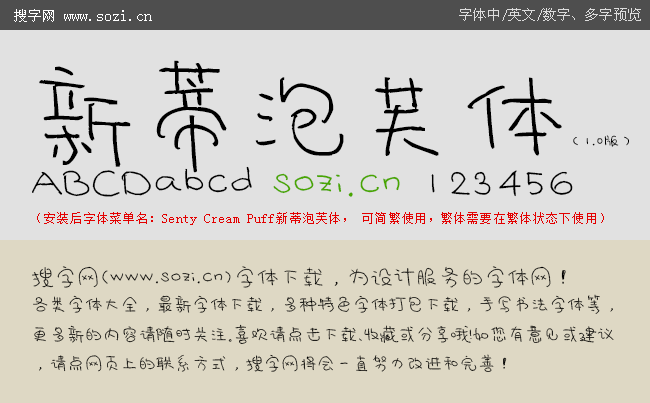
新蒂泡芙體
搜字網(wǎng)提供一款新蒂泡芙體中文字體下載,新蒂泡芙體是一款應(yīng)用于設(shè)計方面的中文簡體漢字,該字體筆畫非常細(xì)膩,整體效果為卡通風(fēng)格,且字庫完整,覆蓋常用簡體、繁體漢字、拉丁字母、數(shù)字等,可用于產(chǎn)品設(shè)計、包裝印刷、報刊雜志、繪畫創(chuàng)作等廣告設(shè)計場合使用,喜歡的朋友快下載收藏吧。